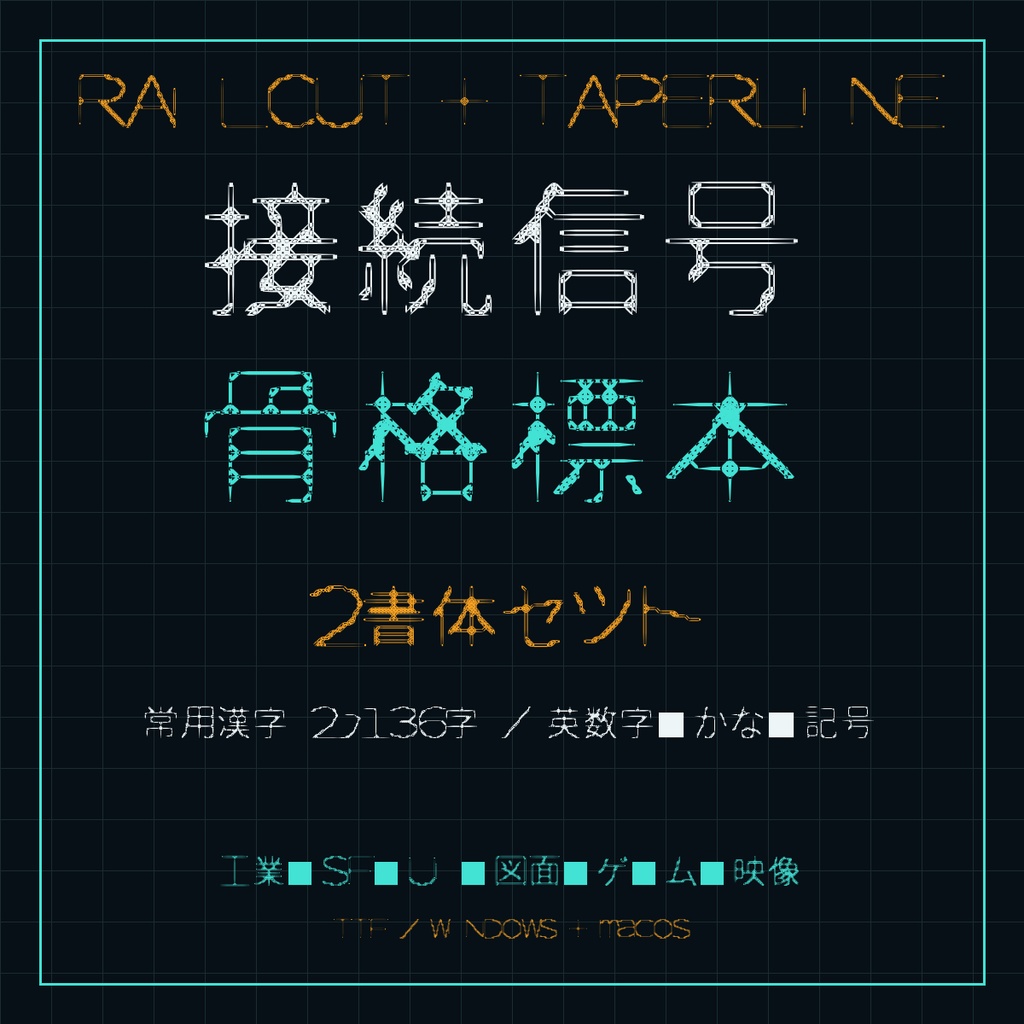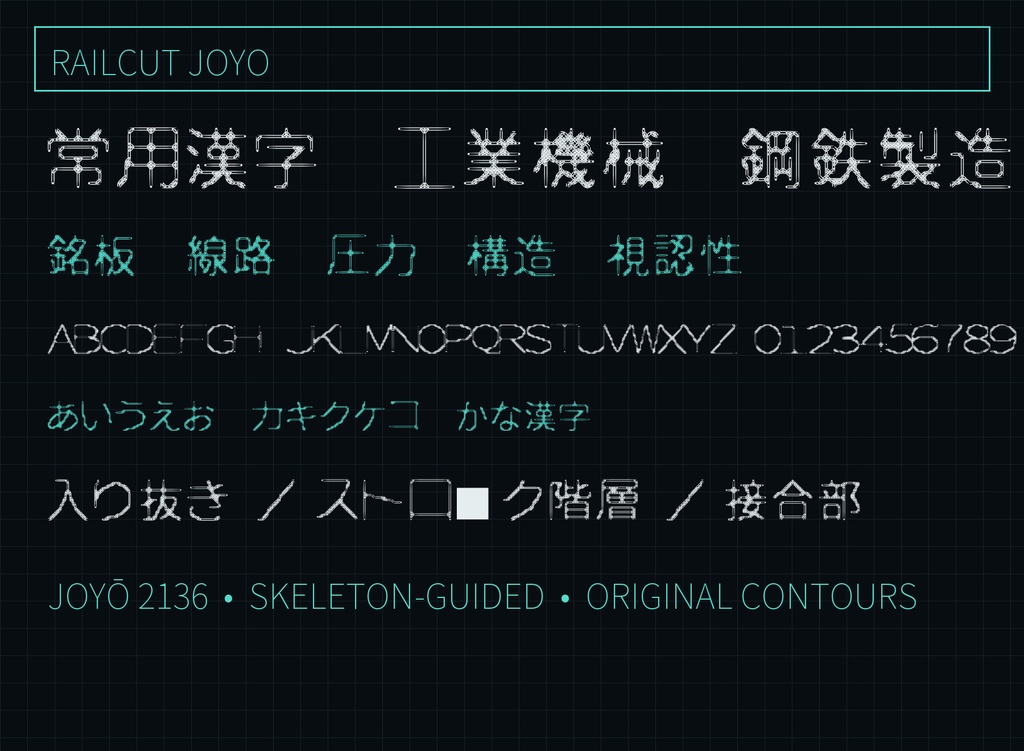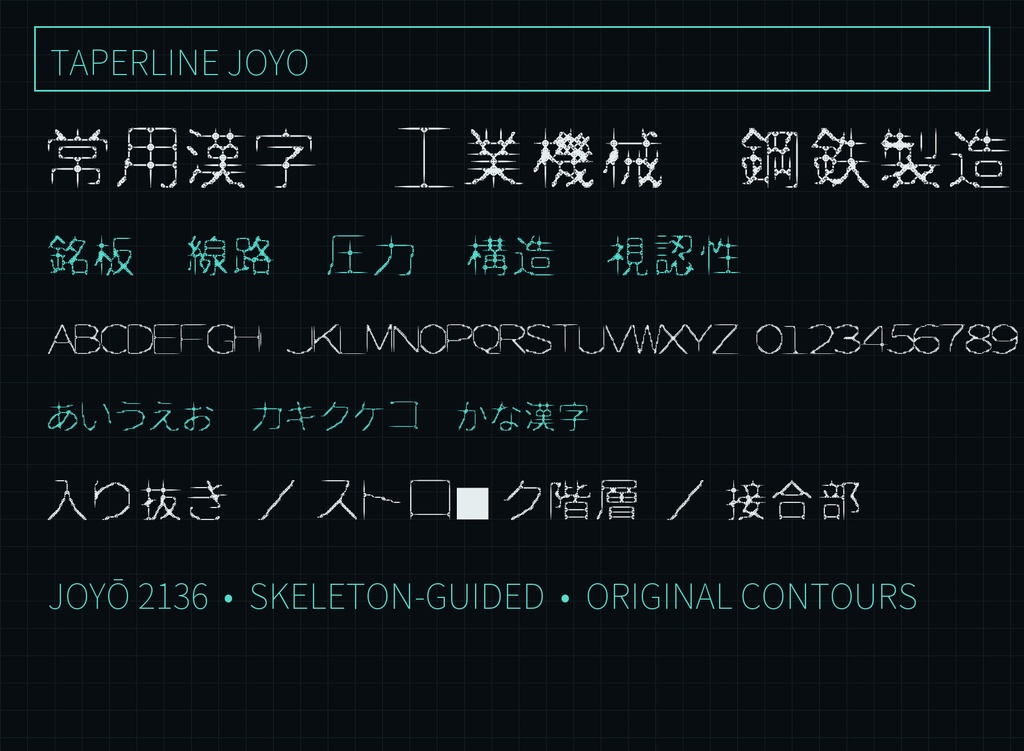
【RAILCUT + TAPERLINE】接点・骨格系 日本語フォント2書体セット|常用漢字2,136字収録
【RAILCUT + TAPERLINE 日本語フォント2書体セット】 線路、端子、接点、骨格標本を思わせる構造で文字を組み立てた、日本語ディスプレイフォントの2書体セットです。 RAILCUTは切断されたレールと接続点を強調した硬質なデザイン。TAPERLINEは字画の入口と出口を尖らせ、信号図・配線図のようなリズムを持たせています。 工業、SF、サイバー、ゲームUI、図面、映像タイトル、ロゴ、展示グラフィックに。 ■ 価格 1280円 ■ 内容 RailcutJoyo-Regular.ttf TaperlineJoyo-Regular.ttf ■ 形式 TrueType(TTF) / Windows・macOS ■ 収録 各書体 2408文字 常用漢字:各2136字 ひらがな・カタカナ・英数字・基本記号 ■ 利用 個人・商用利用可。ロゴ、動画、ゲーム、印刷、配信、同人・商業作品に使用できます。クレジット不要。フォントデータの再配布・共有・転売は禁止です。詳細はZIP内の利用規約をご確認ください。 ※見出し・タイトル向けの装飾書体です。細線を含むため、小サイズでの使用時は事前に出力をご確認ください。